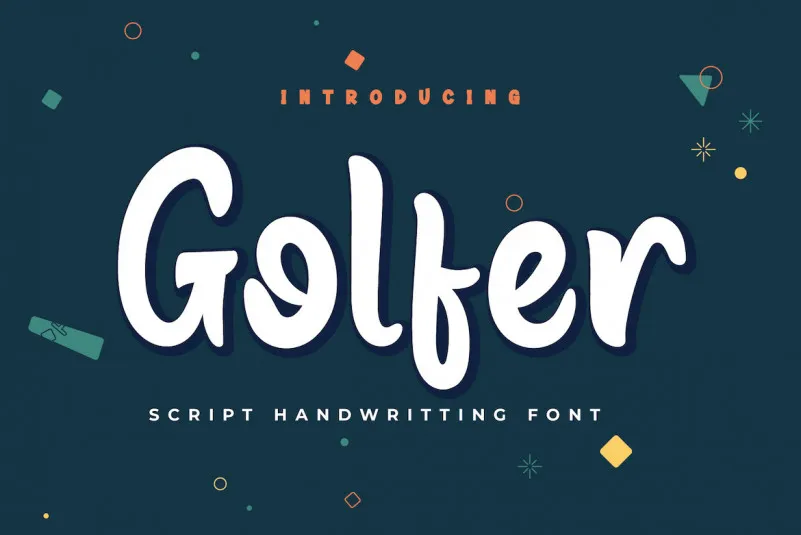
A fonte Golfer é uma criação minimalista e elegante que captura a essência do designer productype. Ela está projetada para transmitir tranquilidade com sua tipografia suave, mas ao mesmo tempo bela e refinada. Esta escolha de fonte se destaca especialmente em tarefas designísticas especiais, como textos e cabeçalhos, proporcionando um visual atraente que se destaca na página do seu projeto. Suas linhas curvas e sutis permitem ao designer explorar designs criativos sem comprometer a legibilidade, tornando-a uma opção excelente para aqueles buscando uma fonte moderna com uma personalidade única. Seja em aplicativos digitais ou impressões gráficas de alta qualidade, Golfer oferece um toque diferenciado que certamente enriquecerá sua identidade visual.
Designer: productype